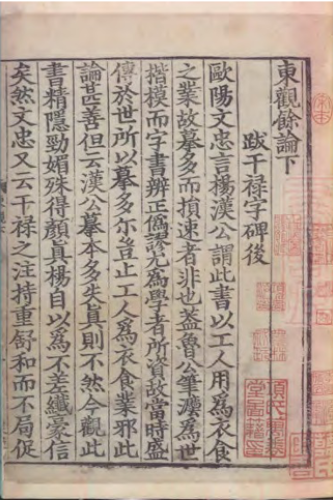
上图东观体可用于非盈利目的各类场景,这款字体结构工整、笔画清晰,兼顾美观与易读性,适用于标题、正文、海报、包装、LOGO 等多种场景。字形优雅稳定,风格百搭耐看,适配日常排版与创意设计,让文字呈现更舒适、更具质感。上图东观体可用于非盈利目的各类场景一笔一画,皆是细节,以均衡的比例、流畅的线条打造舒适视觉体验,字形端正大气,风格简约现代。无论是商业设计、品牌宣传还是日常排版,都能轻松驾驭,让文字更有格调与力量。上图东观体可用于非盈利目的各类场景字体下载。
2023年4月,上海图书馆联合汉仪字库定制的专属字体“上图东观体”完成制作,经过内部测试后,现正式向社会发布。这套字体包含常规、细体和粗体三种规格字重,每种字重覆盖9169个字符,历时一年悉心打磨而成。富有书卷气和书写感的“上图东观体”,旨在为数字时代的阅读者和创作者保留见字如面、执笔抵心的文化传统与温度。
东观,是东汉宫廷中收藏典籍、校书著述的处所,功能近似今天的图书馆。字体取“东观”之名,也因为设计灵感源于上图的丰富馆藏,尤以《东观余论》《长短经》和《唐诗百名家全集》三部字体风格端庄俊逸的古籍为主。
专属字体的开发,旨在提升上海图书馆视觉形象的辨识度与组织文化的统一性,也兼顾了数字排版的现实需求与传统手书蕴含的视觉美感。整套字体的设计结合了上图为迎向大阅读时代设定的“智慧、包容、互联”3i转型战略,智慧排布字体重心与字面比例,令字身修长儒雅;包容多样化应用场景和全年龄段视觉需求;互联传统手书韵味与现代字体结构,为广泛读者提供有底蕴、具温度、会呼吸的阅读体验。
源 起
上图专属字体取材于上图馆藏宋代经典古籍善本《东观余论》(宋嘉定三年1210年)、《长短经》(北宋刻本),以及清代古籍《唐诗百名家全集》(清康熙四十七年1708年仿宋刊本)。
字体风格上,《东观余论》和《长短经》均属浙江刻本,笔画较粗字形端庄,而《唐诗百名家全集》为清仿宋本字形,笔画较细俊朗清秀。
通过对上图《东观余论》、《唐诗百名家全集》和《长短经》三本古籍字体特点提炼并创新,设计一款具有“书卷气”的上图专属字体。
《唐诗百名家全集》 (清康熙四十七年1708年仿宋刊本)
《长短经》 (北宋刻本)
《东观余论》 (宋嘉定三年1210年)
书写感
细体的水和春选取于《唐诗百名家全集》,粗体的字和东字来自于《东观余论》,字体设计时保留原帖中的书写感,修正了字形,使字体具有优雅亲和感。上图东观体可用于非盈利目的各类场景
保留原贴的笔形处理
保留原帖中的笔形处理方式,如言字的竖点,时的竖收笔,碑的收笔等处理效果,使字体具有独特性和文化性。